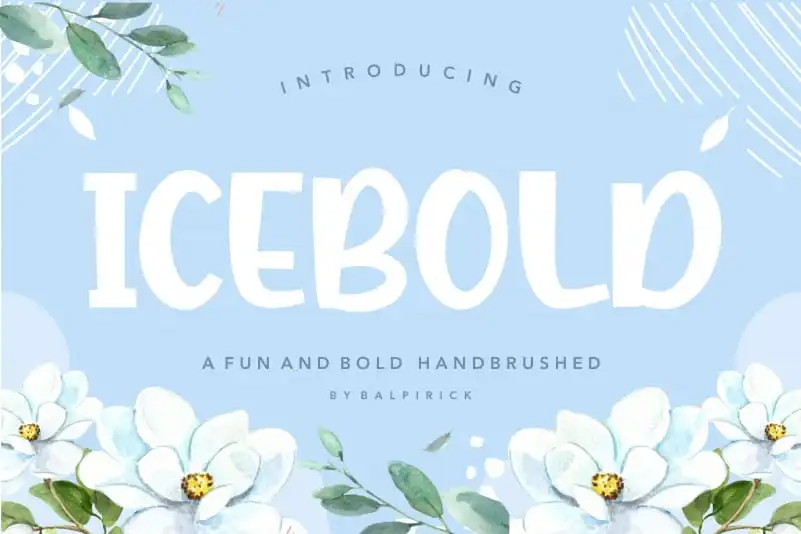
ICEBOLD Fun and Bold Handbrushed Font – Download Grátis
A fonte ICEBOLD Fun and Bold Handbrushed é perfeita para quem busca uma opção divertida e moderna que se destaca no mundo digital. Ideal tanto para uso em embalagens de produtos, como em projetos de marca, revistas, mídia social, casamentos ou qualquer outra ocasião onde você deseja destacar os textos acima do fundo, ICEBOLD é uma escolha inconfundível. Com sua design sensacional e estilo artesanal, a ICEBOLD oferece um toque moderno que combina harmonicamente com as mais variadas aplicações. Seu desenho elaborado e elegante, mas também seu tom descontraído e vibrante, tornam esta fonte uma ótima opção para projetos onde você deseja expressar entusiasmo ou criar um impacto visual atraente. Com ICEBOLD Fun and Bold Handbrushed Font, seus trabalhos em design digital ficarão ainda mais atraentes. Essa elegante mão-de-obra brush é perfeita para quem busca uma fonte que seja tanto funcional quanto criativa. Não espere mais e descubra o poder de ICEBOLD Fun and Bold Handbrushed – sua fonte de sucesso para qualquer projeto visual.